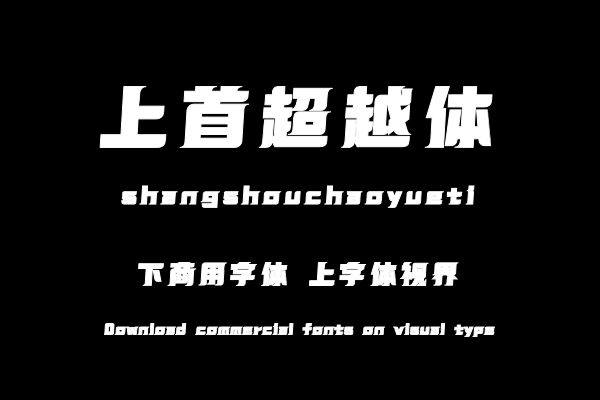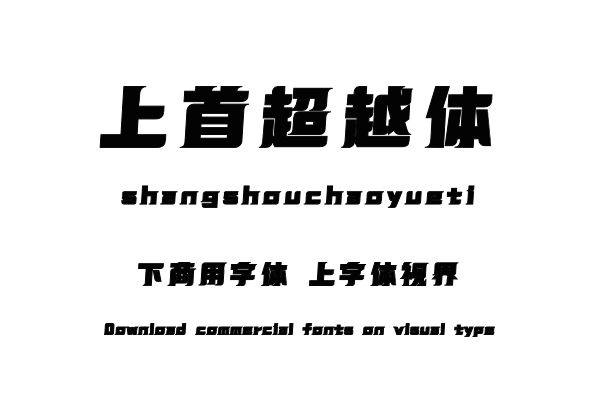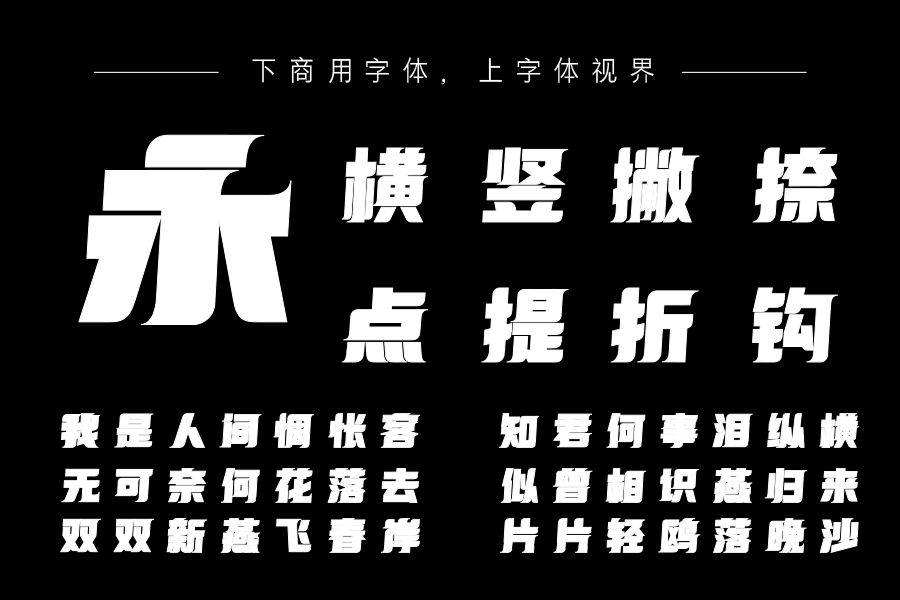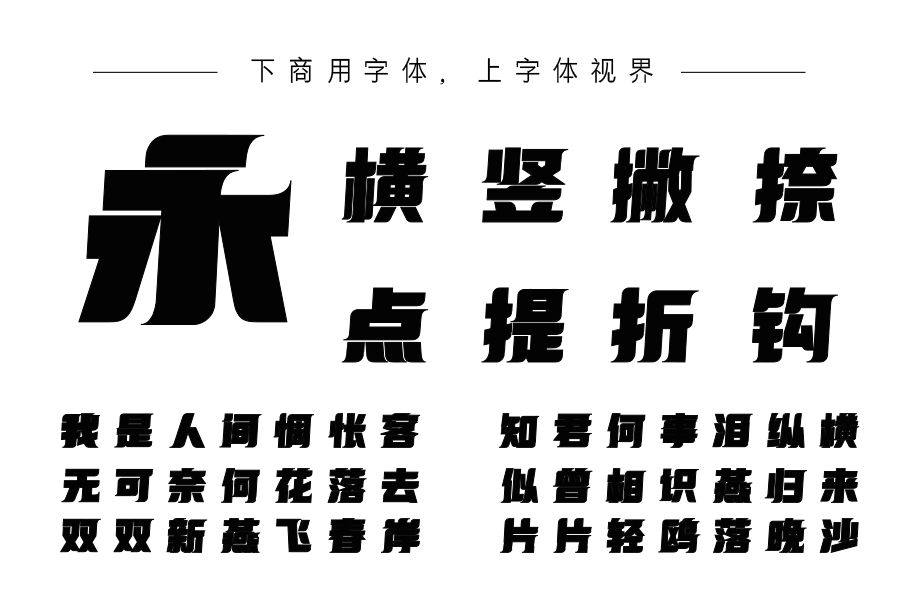
上首超越体,整体风格简洁,将笔画进行变形,横笔和转角处做圆角处理,让字体更加稳重。把字体进行倾斜处理,并在上面添加尖角特点,可以进一步加强字体的画面效果,让字体......购买须知:“下载服务费”与“字体VIP”所获得字体 仅用于个人非商用, 商用请联系付费授权。本字体为电脑用字,手机没有root权限不支持直接手机换字(手机如何root,请自行百度搜索教程)。购买前请先 了解清楚后再付款 ,字体为虚拟产品无法回收 一旦购买不支持退款。